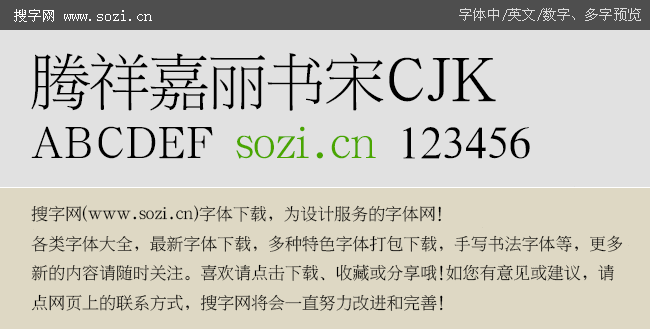
騰祥嘉麗書宋CJK
搜字網(wǎng)提供一款騰祥嘉麗書宋CJK中文藝術(shù)字體下載,騰祥嘉麗書宋是一款簡潔的宋體字體,該字體線條纖細(xì)精致,字形大方得體,整體效果出眾,并且字庫完整,可用于藝術(shù)設(shè)計(jì)、包裝印刷、簽名設(shè)計(jì)、圖形設(shè)計(jì)等領(lǐng)域。